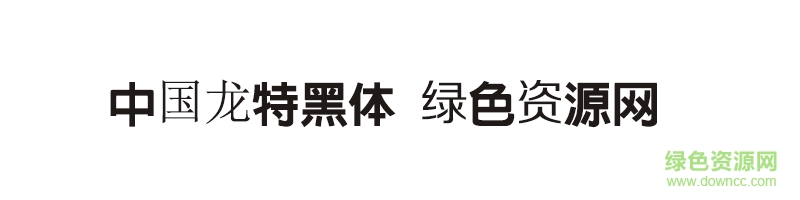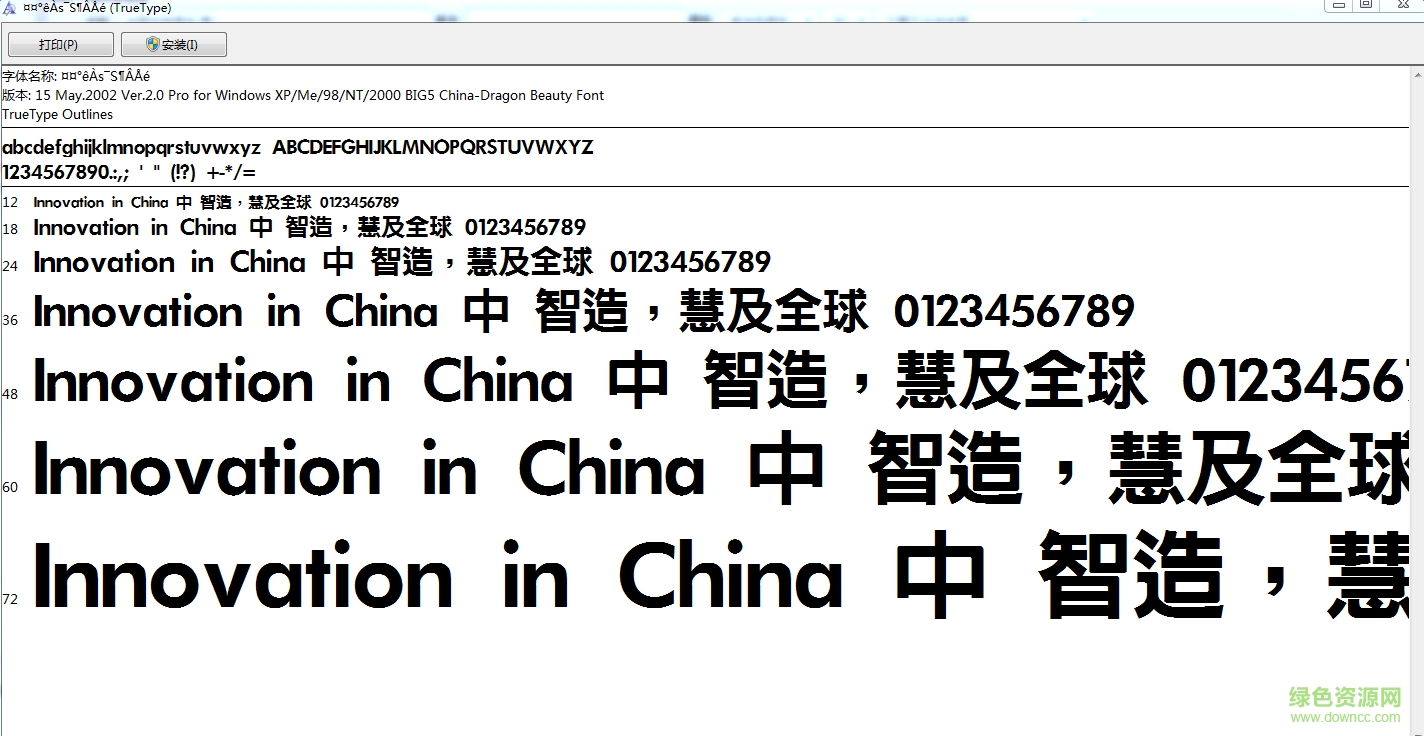
中國(guó)龍?zhí)?a href="http://573ee.cn/k/heitizitixzdq/" target="_blank">黑體字體是一款中國(guó)風(fēng)十足的字體軟件,小編為各位喜歡中國(guó)龍字體的朋友們獻(xiàn)上寶貴資源,還有更多其他風(fēng)格字體,在綠色資源網(wǎng)都能找到哦!
在藝術(shù)設(shè)計(jì)和各種商業(yè)海報(bào)的制作中,字體的風(fēng)格選擇是十分重要的,不同的風(fēng)格字體都會(huì)造就不同的視覺效果。而中國(guó)龍字體是一套充滿中國(guó)風(fēng)的中文字庫,綠色資源網(wǎng)給大家提供好看的中國(guó)龍?zhí)睾隗w字體!